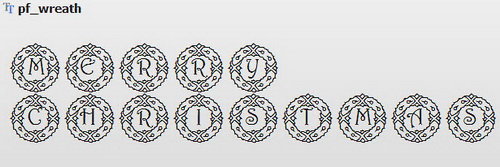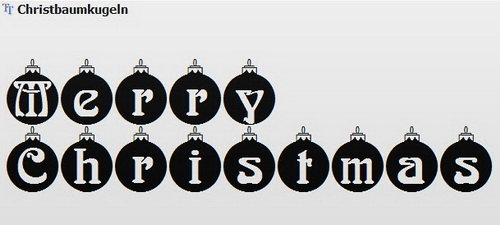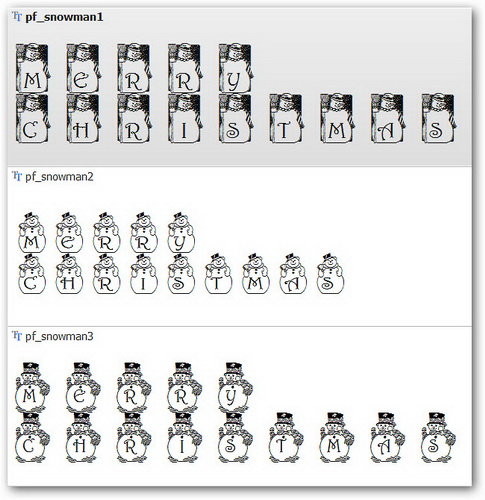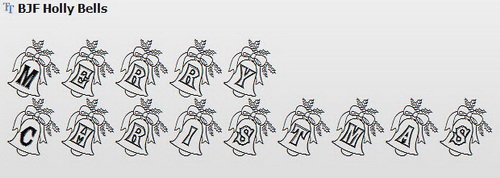
Oldchristmas
Holly
Christmas Flakes
Frosty
Kingthings Christmas
Lung linh huyền ảo của màu sắc những ánh sao Giáng sinh, bạn có thể vào đây để tải font độc đáo này về.
Candy Time
Hình ảnh những thanh kẹo Noel được đưa vào kiểu font này trông rất độc đáo và thú vị. Bạn vào đây để tải font về.
BodieMF Holly
Snowflake Letters
Kiểu font này thật tuyệt vời nếu bạn muốn viết thư chúc Giáng sinh, có thể vào đây để tải về.
Hultog Snowdrift
Với những hạt tuyết bố trí dưới dạng bóng của chữ, nó sẽ mang không khí lạnh lẽo trong ngày Giáng sinh đến với bạn. Bạn vào đây để tải font này về.
AlphaShapes Xmas Trees
Với ý tưởng những cây thông noel, đây là kiểu font chữ khá hấp dẫn với bạn. Bạn có thể vào đây để tải về, hoặc vào đây để tải kiểu font Christmas Tree tương tự.
PF Snowman
Bao gồm 3 kiểu font khác nhau, bạn có thể vào đây để lựa chọn kiểu font ưa thích và tải nó về.
PF Wreath
Cũng không kém phần hấp dẫn là kiểu font chữ PF Wreath, bạn có thể vào đây để tải về.
BJF Holly Bells
Với những quả chuông chữ hấp dẫn, đây là một món trang trí tuyệt vời cho ngày Giáng sinh đang đến gần. Bạng có thể vào đây để tải font chữ về.
Christbaumkugeln